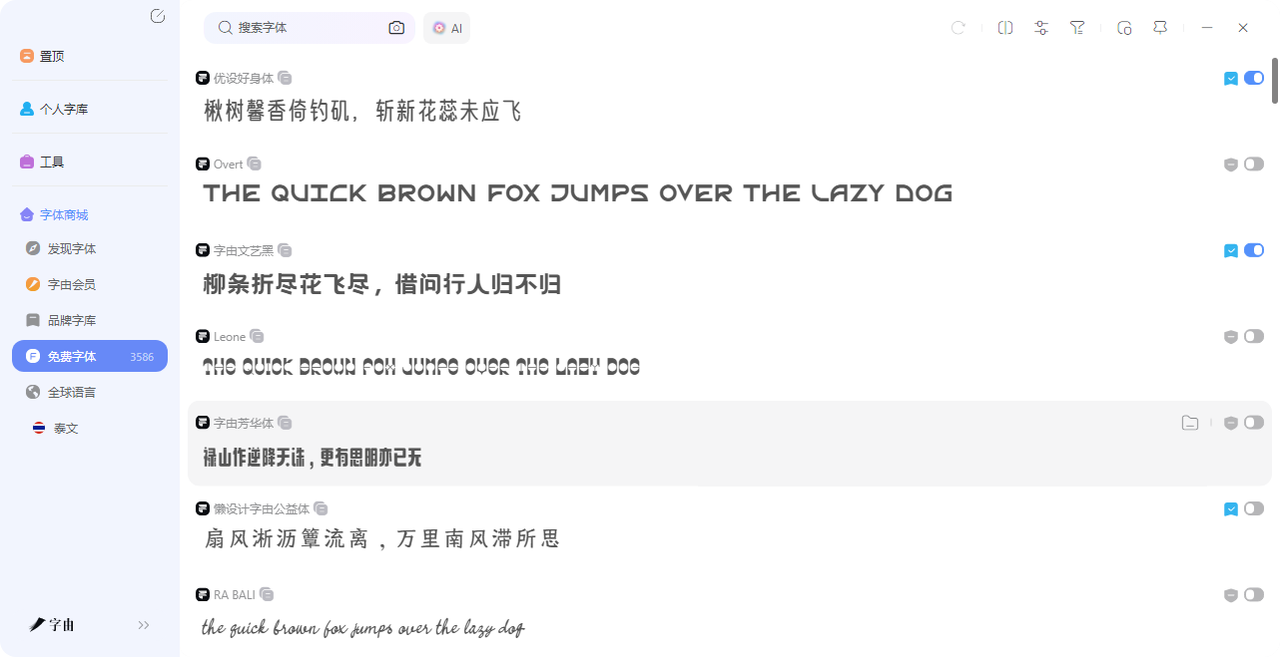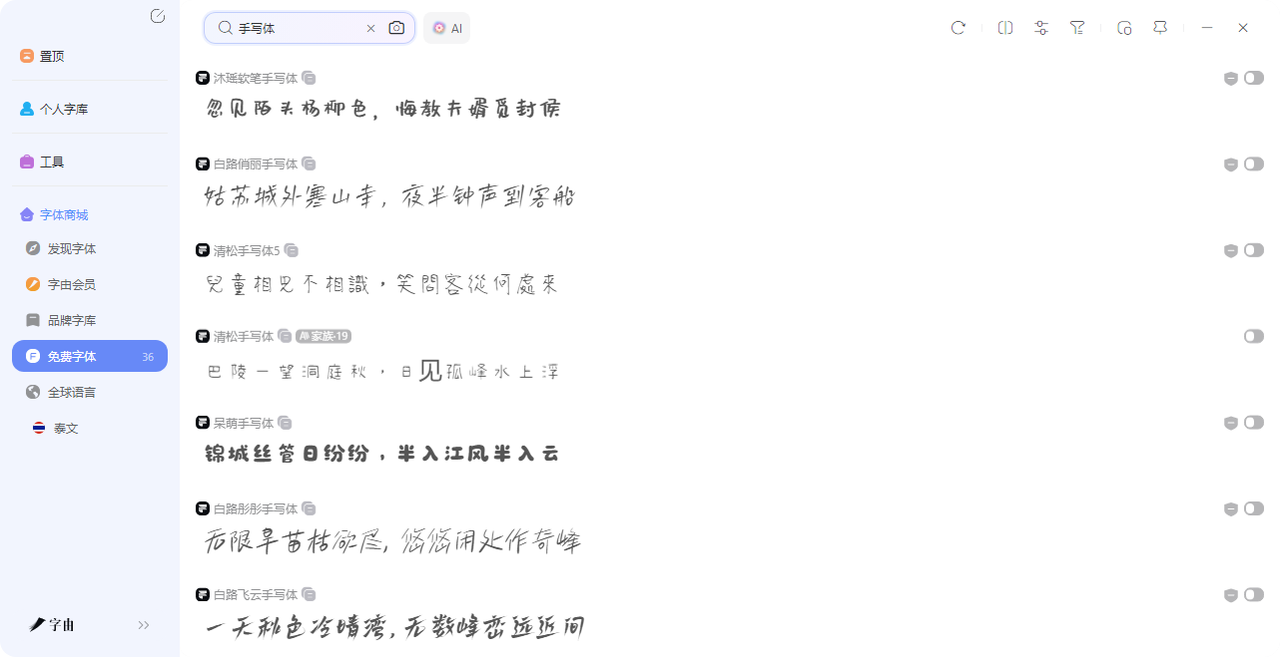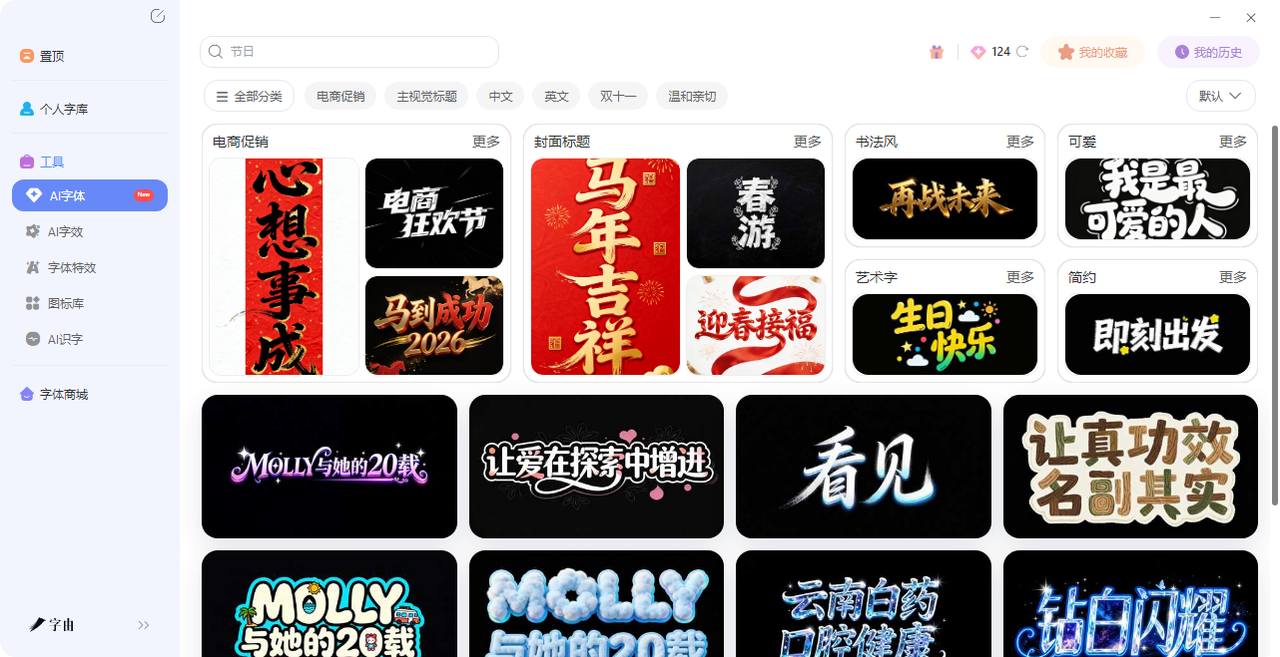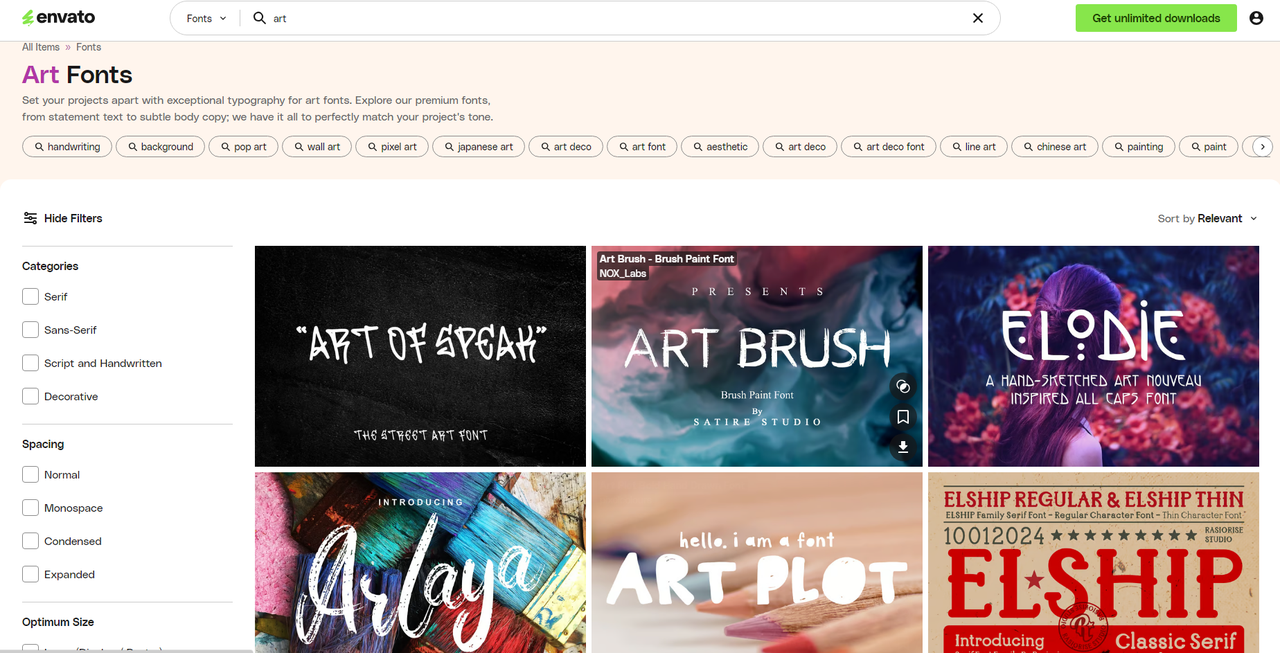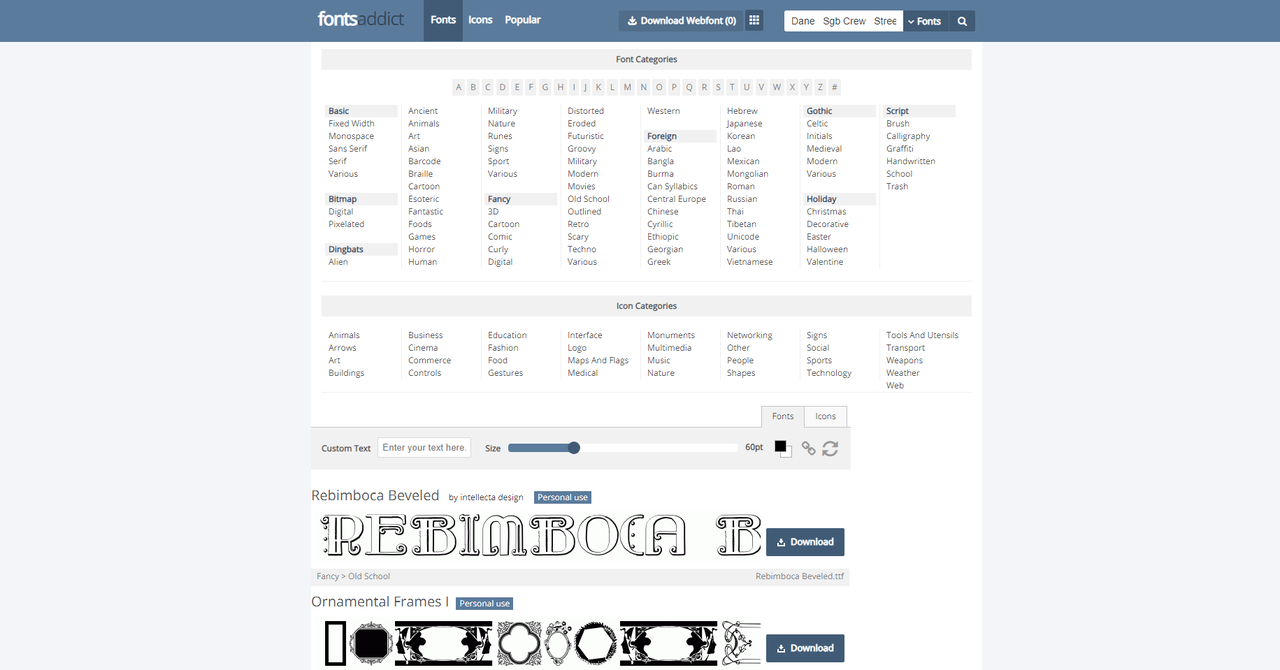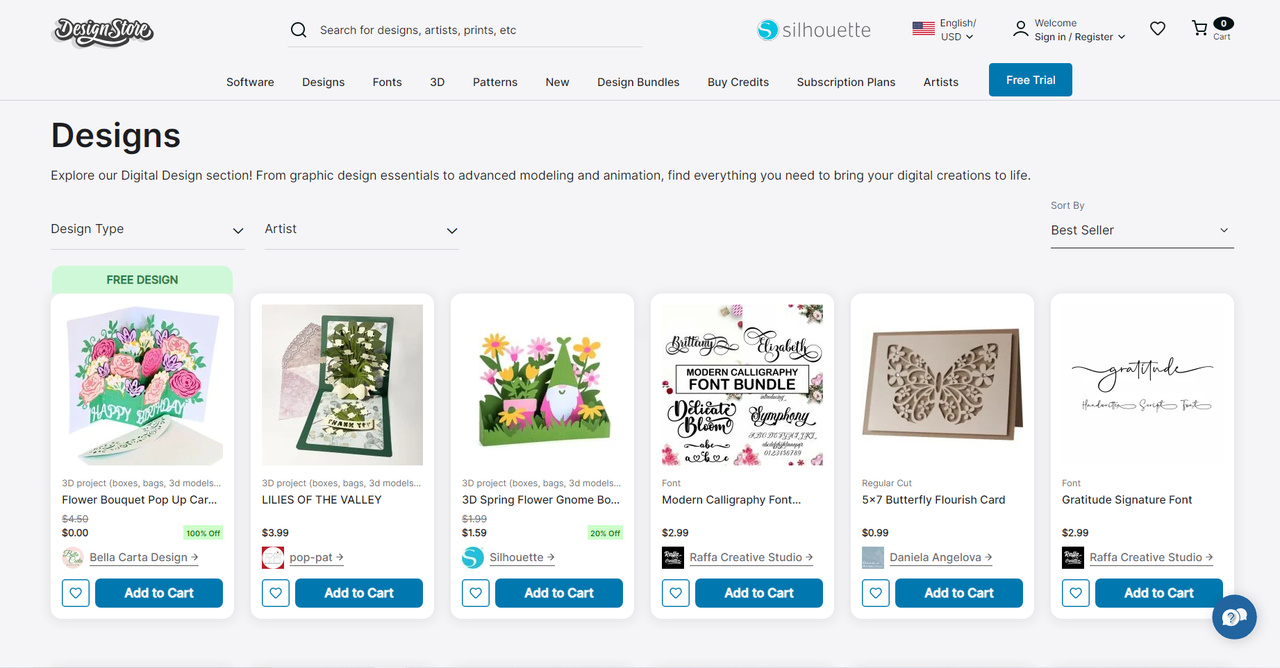
个性字体去哪找?这5个网站让你的文字与众不同
你有没有过这种经历:做了一张海报,排版、配色都挺满意,但标题那几个字怎么看怎么别扭——不是字体太普通,就是风格跟整体不搭。想换个有个性一点的字体,打开电脑字体列表翻来翻去,全是基础款字体。但是有一点你忽略了,网上有着大量个性字体资源站,从免费商用到设计师私藏,从手写体到涂鸦风,从复古到科幻,应有尽有。今天整理了5个高质量的个性字体网站,每个站都有自己的特色,帮你快速找到让文字与众不同的那一款。
你有没有发现,大家做海报翻来覆去就是那几款免费字体?不是不想用个性的,是根本不知道去哪找、找到了又怕版权问题。字由解决的就是这个“找不到、不敢用”的痛点。它把上万款字体——包括大量小众、有设计感的个性字体——整合到一个平台上,而且每款字体的授权信息都标注得清清楚楚。字由的筛选栏里,光“字体类型”就有十几种分类:黑体、宋体、楷书、书法体、手写体、圆体、
创意字体、装饰字体……勾选“创意字体”或“装饰字体”,出来的全是不走寻常路的款式。
比如你搜“手写体”,普通网站可能只有三五款,字由里能翻出几十款风格迥异的手写体——有的像钢笔随手写,有的像毛笔蘸墨,有的带着涂鸦的随意感。
还有一个“热度排序”功能特别实用。你可以选择按“热度从低到高”排序,专门挑那些用的人少、还没被“用烂”的小众字体。这些字体可能藏在库的深处,但翻出来就是宝藏。
除了正常字体,还有字由的AI字体可以使用:
字由的AI字体功能可以直接帮你“造”出一张个性字体图片。打开客户端,找到“工具”里的“AI字体”,里面有400多种特效模板——国潮风、霓虹灯、金属质感、手写书法、涂鸦风……选一个你喜欢的模板,输入你的名字或文案,点“立即生成”,30秒左右就能得到一张设计好的艺术字图片。
2、Art Fonts
第二个网站叫Art Fonts,这是一个专门展示和销售艺术字体的平台,分类包括Serif(衬线体)、Sans-Serif(无衬线体)、Script and Handwritten(手写体)、Decorative(装饰体)等。每个字体都有详细的预览图和介绍,比如截图中展示了“MightyFire_STD”、“ART OF SPEAK”、“ART PLOT”、“ART BRUSH”等艺术字体。这个站的特点是“精”——它不像那些聚合站动辄几万款字体,而是精选了设计感较强的艺术字体,适合对字体品质有要求的用户。每款字体都标注了风格属性,比如手写、涂鸦、像素、日本艺术、装饰艺术等,还可以按间距(正常、等宽、紧缩、扩展)和尺寸(大标题、小正文)筛选。
如果你需要找一款有艺术感的标题字体,或者想看看专业设计师都在用什么风格的字体,Art Fonts值得翻一翻。需要注意的是,这个站上的
3、fontsaddict
第三个网站叫fontsaddict。这是一个功能极其强大的字体聚合站,最大的卖点是分类细致到令人发指。截图显示它的分类包括:Basic、Ancient、Military、Distorted、Western、Hebrew、Gothic、Script、Fixed Width、Animals、Nature、Eroded 等,除了字体,fontsaddict还提供图标分类。搜索框下面可以输入自定义文字预览效果,调整字号,然后下载。授权方面,每个字体页面会标注是个人使用还是免费商用,下载前需要确认。如果你是一个喜欢按风格翻字体的设计师,fontsaddict的分类体验比那些只有一个搜索框的网站好太多。
4、Designs
第四个网站叫Designs,这是一个综合性的设计资源平台,包含字体、3D模型、设计模板等。字体板块展示了多款创意字体,比如“Modern Calligraphy Font”、“Delicate Bloom”、“Butterfly Blossom”、“Grafitude Signature Font”等,风格覆盖现代、优雅、复古、粗体、手写等。这个站的特点是“折扣”——截图显示很多字体和设计资源都有大幅优惠,有的甚至100% Off(免费)。如果你预算有限,但又想要高质量的创意字体,可以多关注这个站的免费或打折资源。每款字体都有详细的预览和“Add to Cart”按钮,购买后可以直接下载。
5、FontsIsland
第五个网站是FontsIsland,他的“Art fonts”分类下共有1074款字体。首页展示了Ambassador、ArbatC、Mrs Onion Monsters、Sony [Rus by me]、ArtModernAP、Kelvinch等字体,每款都标注了下载次数(从几千到几十万不等)。FontsIsland的分类也很丰富:西里尔字体、罗马字体、免费字体、个人免费使用、替代字体、品牌字体、
复古字体、东方字体、哥特字体、
涂鸦字体、装饰字体、情人节字体、设计字体……几乎覆盖了所有场景。
选个性字体网站,核心就看三点:字体够不够多、分类好不好找、授权清不清晰。如果是字由,你不用下载文件、一键激活,授权标注清楚,适合怕麻烦的用户,如果你只是想偶尔用一下个性字体,字由的免费商用库和激活机制最省事。不管选哪个,用之前记得看一眼授权——个人使用和免费商用是两回事,千万别踩坑。